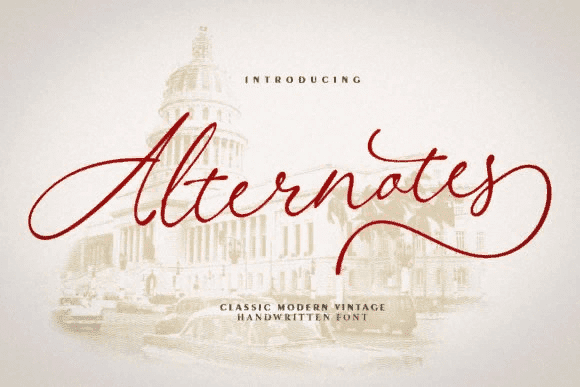
Название: Alternotes Font (2021)
Alternotes - прекрасный шрифт, излучающий игривость и очарование.
Этот шрифт был создан специально для тех, кому нужен красивый и освежающий вид их дизайна.